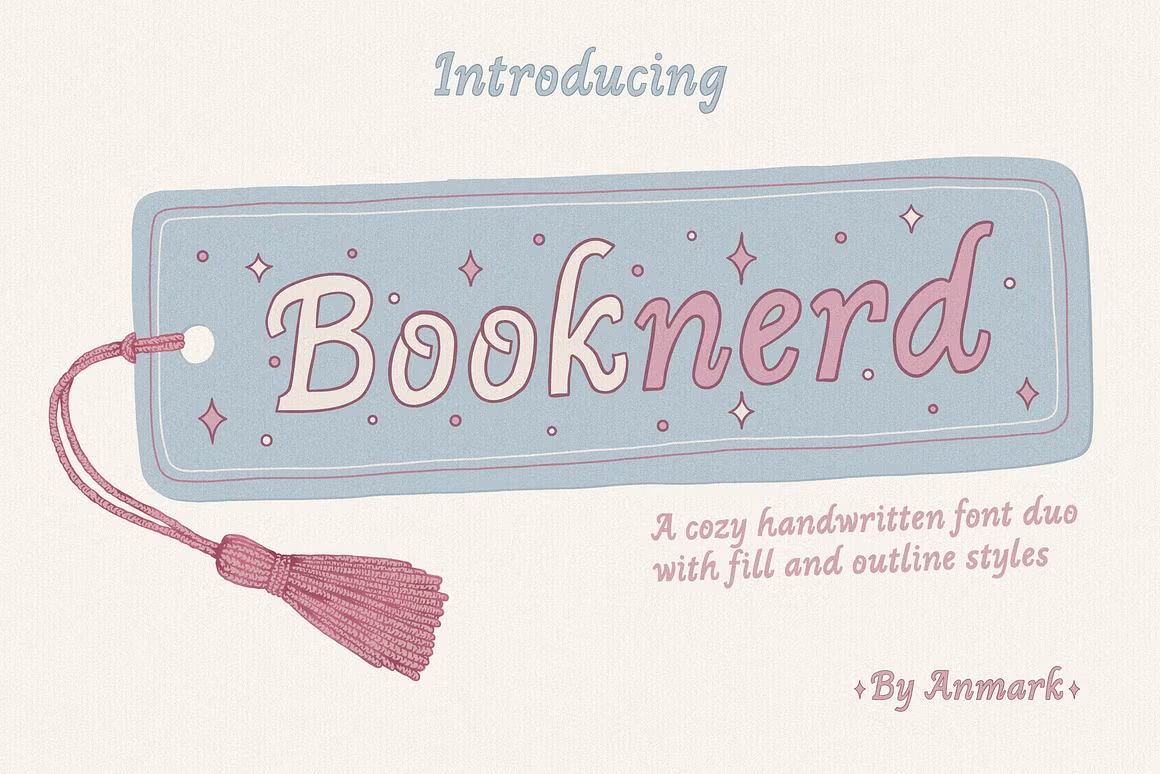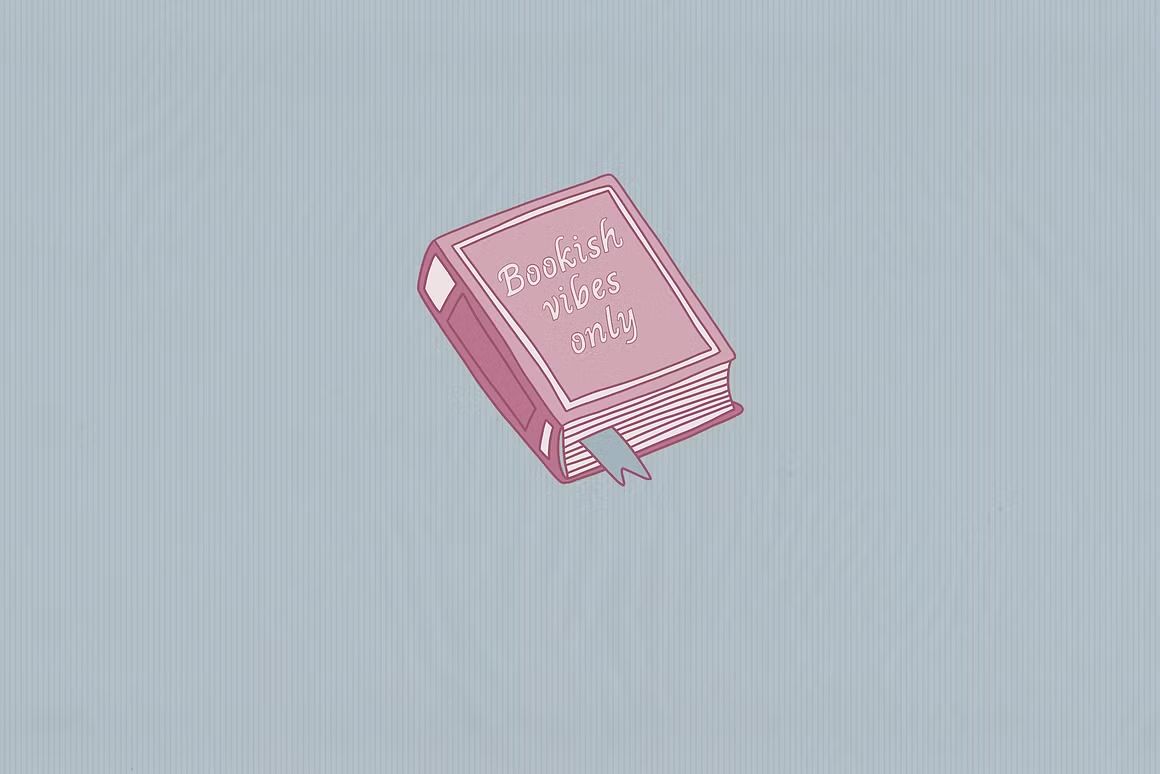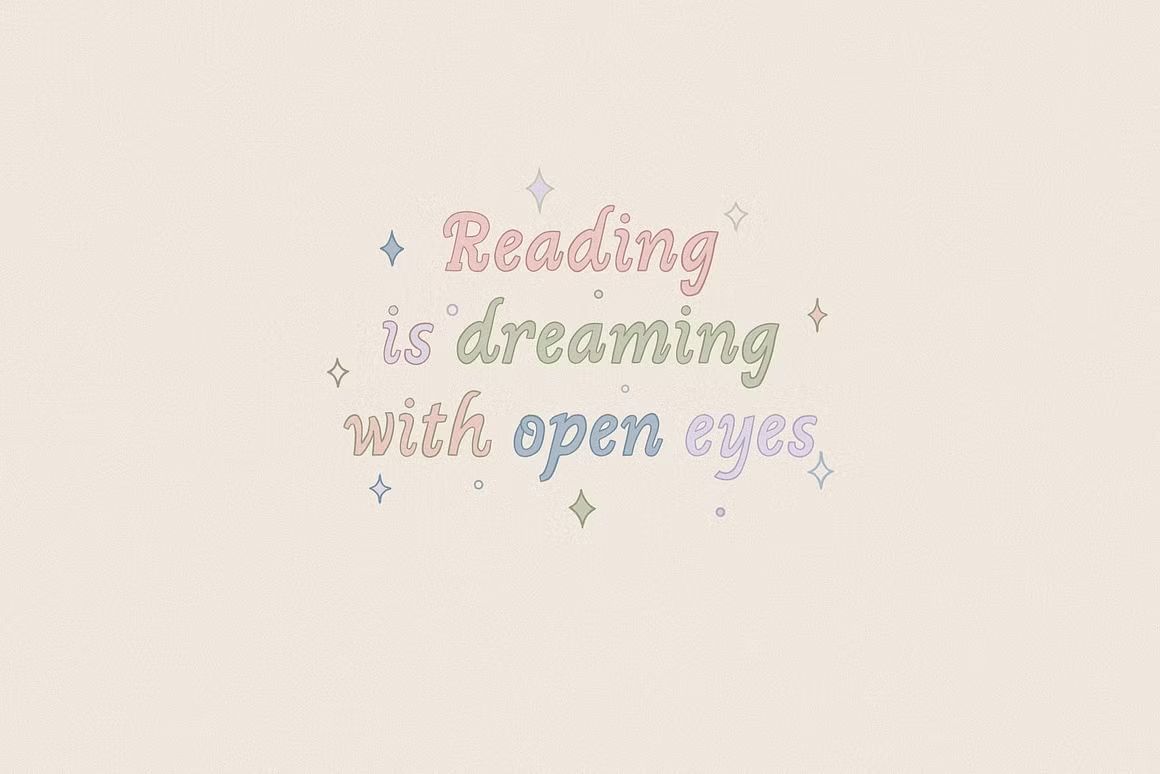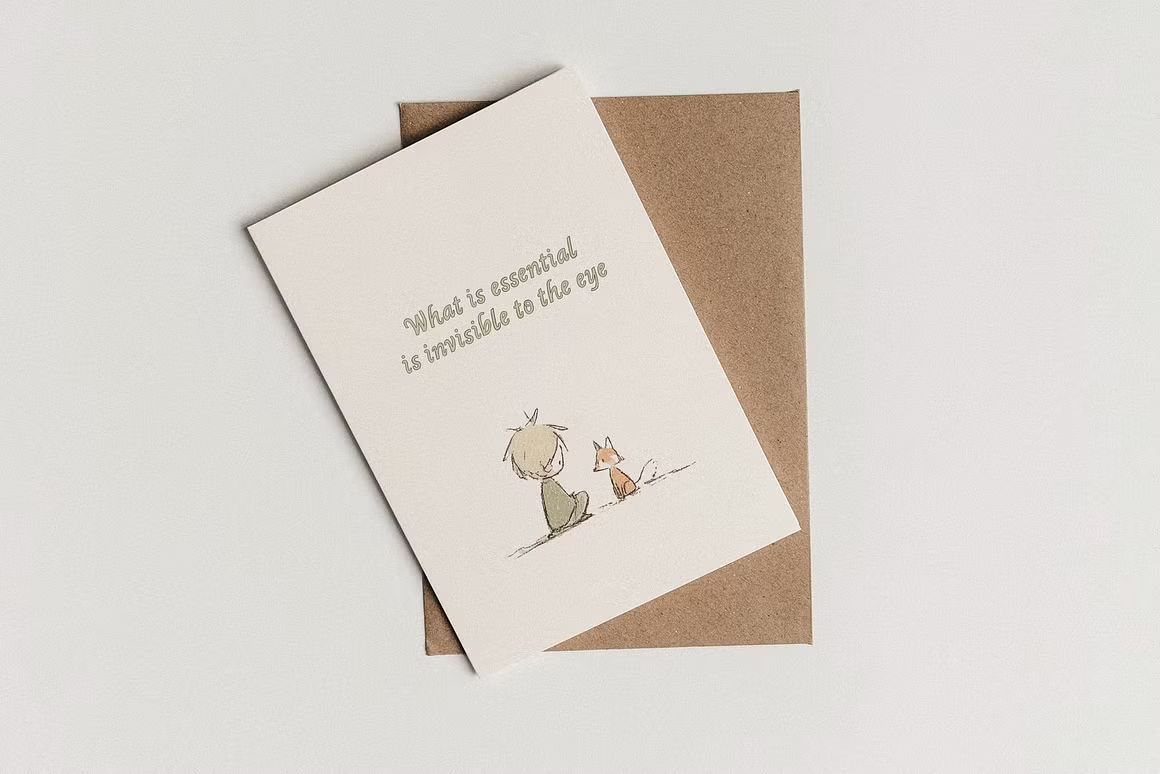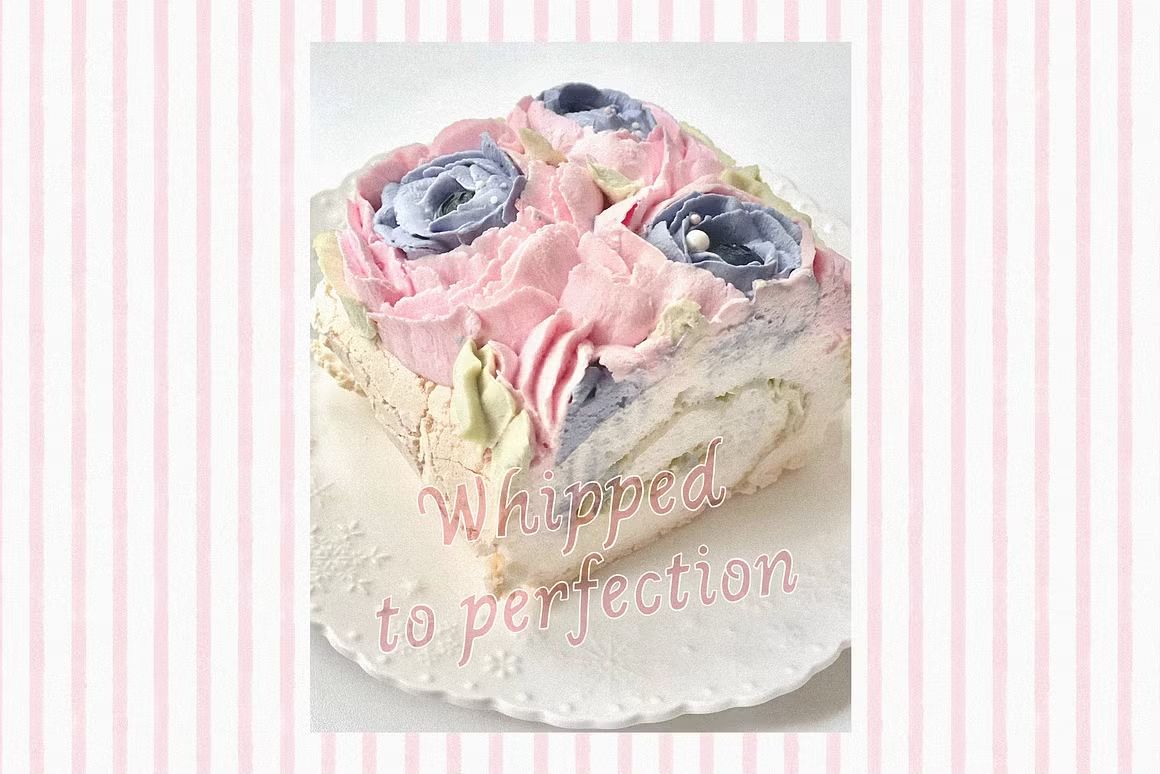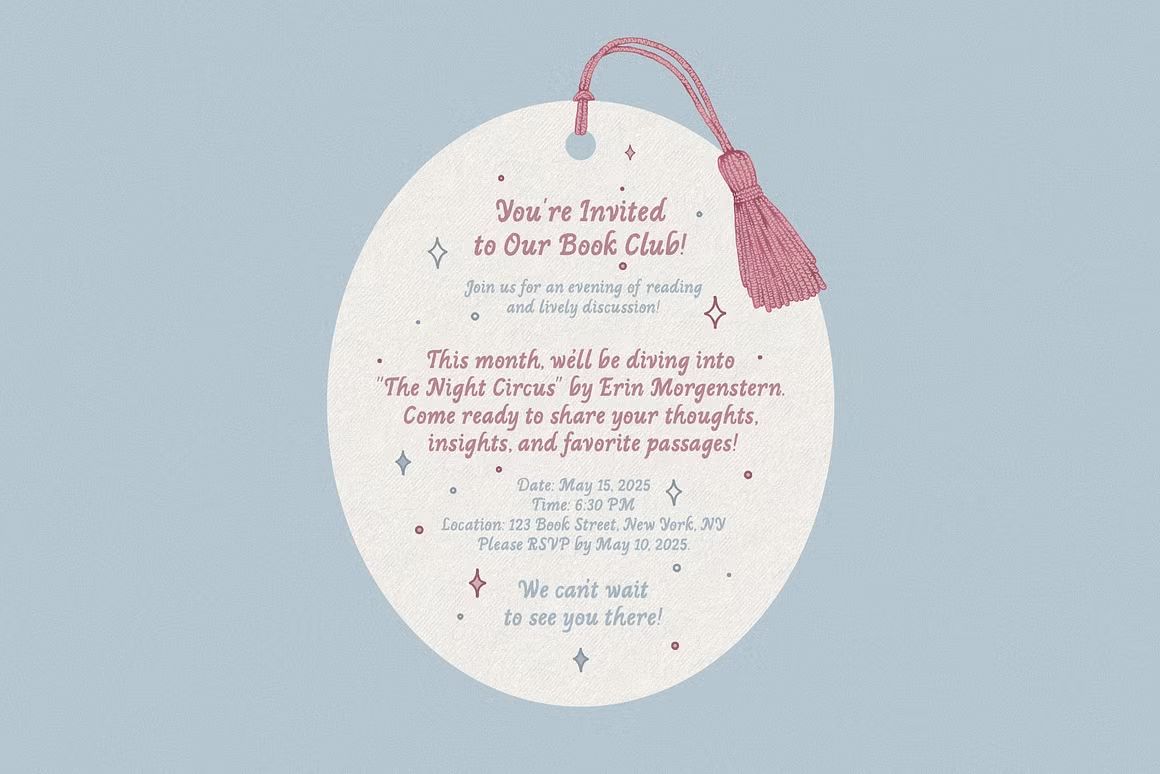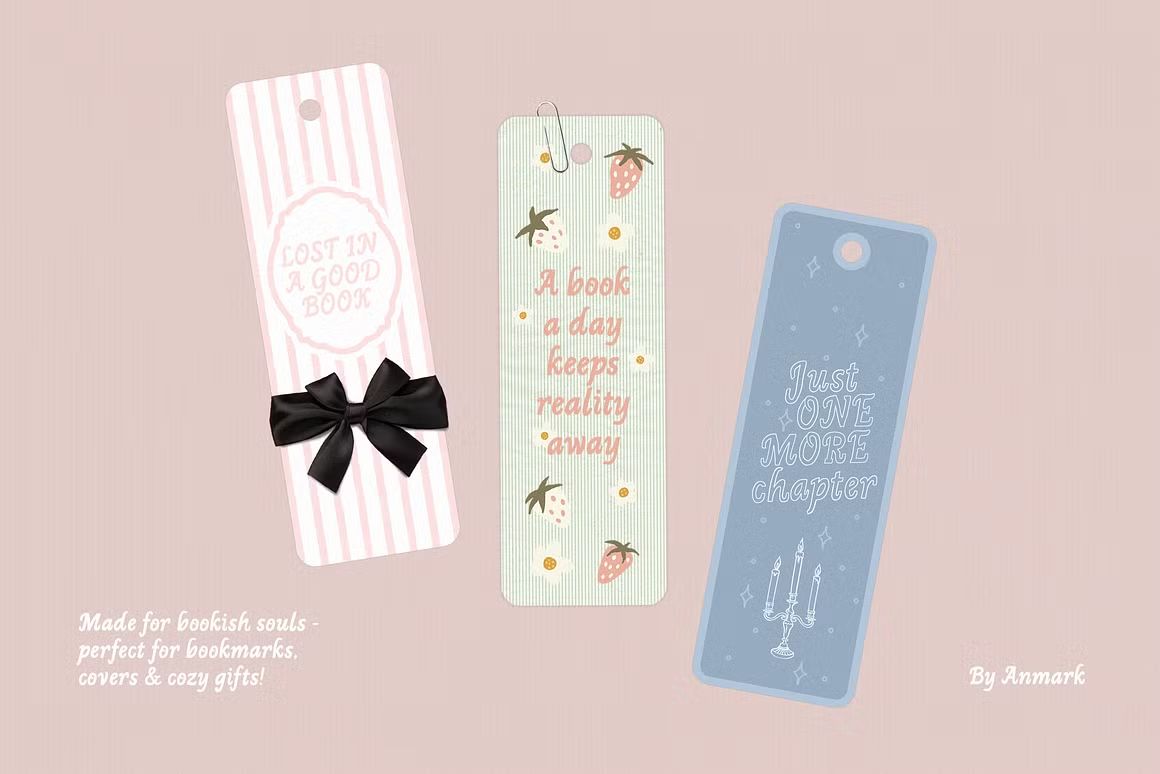
Booknerd – Handwritten Font
Booknerd adalah font handwritten kasual dan rapi, cocok untuk journaling, quotes, dan konten personal. Format OTF/TTF/WOFF, siap digunakan.
Booknerd adalah font handwritten yang terinspirasi dari tulisan tangan ringan dan rapi ala catatan jurnal. Dengan tampilan yang kasual, bersih, dan mudah dibaca, font ini cocok untuk journaling, quotes, buku anak, ilustrasi, hingga konten media sosial. Booknerd memberi kesan personal, ramah, dan cocok untuk proyek yang mengutamakan keaslian dan kehangatan.
• Gaya tulisan tangan kasual dan bersih
• Cocok untuk journaling, quotes, dan ilustrasi
• Termasuk huruf kapital, kecil, angka, dan simbol